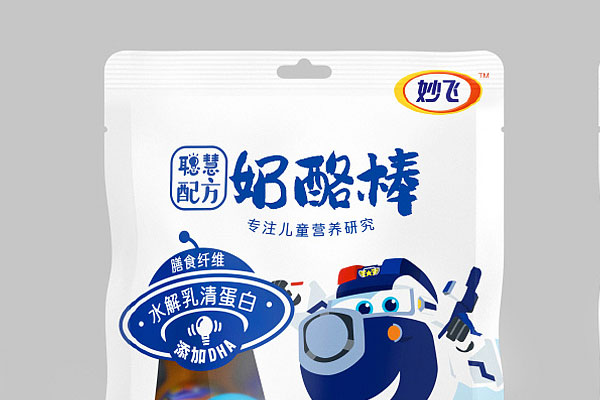
龚帆免费体
龚帆免费体,是由中国成都知名设计师龚帆倾力打造的一款免费商用字体。这款字体包含超过3000个常用简体汉字,为设计师们在包装、电商、漫画、影视综艺、游戏以及各类商业海报和户外广告标题等场景中提供了丰富的选择。
龚帆免费体的设计秉持着简洁大气的理念,每个字形都经过精心雕琢,线条流畅自然,给人一种清新的视觉感受。字体独特的简繁体设计,兼顾了美观与易认性,使得设计师可以根据实际需求灵活选用。
龚帆免费体字体效果预览